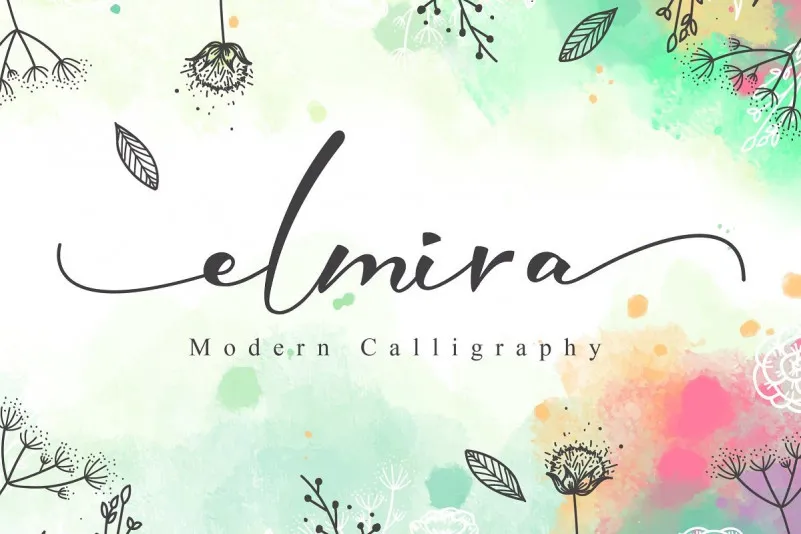
Elmira Script Font – Download Grátis
A Elmsira Script é uma fonte script moderna criada pelo designer 0001themes. Inspirada na arte do caligrafia, essa fonte traz um toque contemporâneo que faz dela perfeita para uso em postais de casamento e materiais de marca. Com seu charme único e sua elegância única, a Elmsira Script oferece uma sensação fresca e moderna. Ideal para aplicar em cartões de aniversário, materiais de marca, cartões de negócios, citações e até mesmo em outdoors e panfletos. Essa fonte é mais do que apenas um formato; ela carrega consigo a essência da caligrafia modernizada, trazendo uma personalidade única à sua criação. Aqui está um material gráfico perfeito para aqueles que buscam uma combinação elegante e fresca em seus projetos digitais.